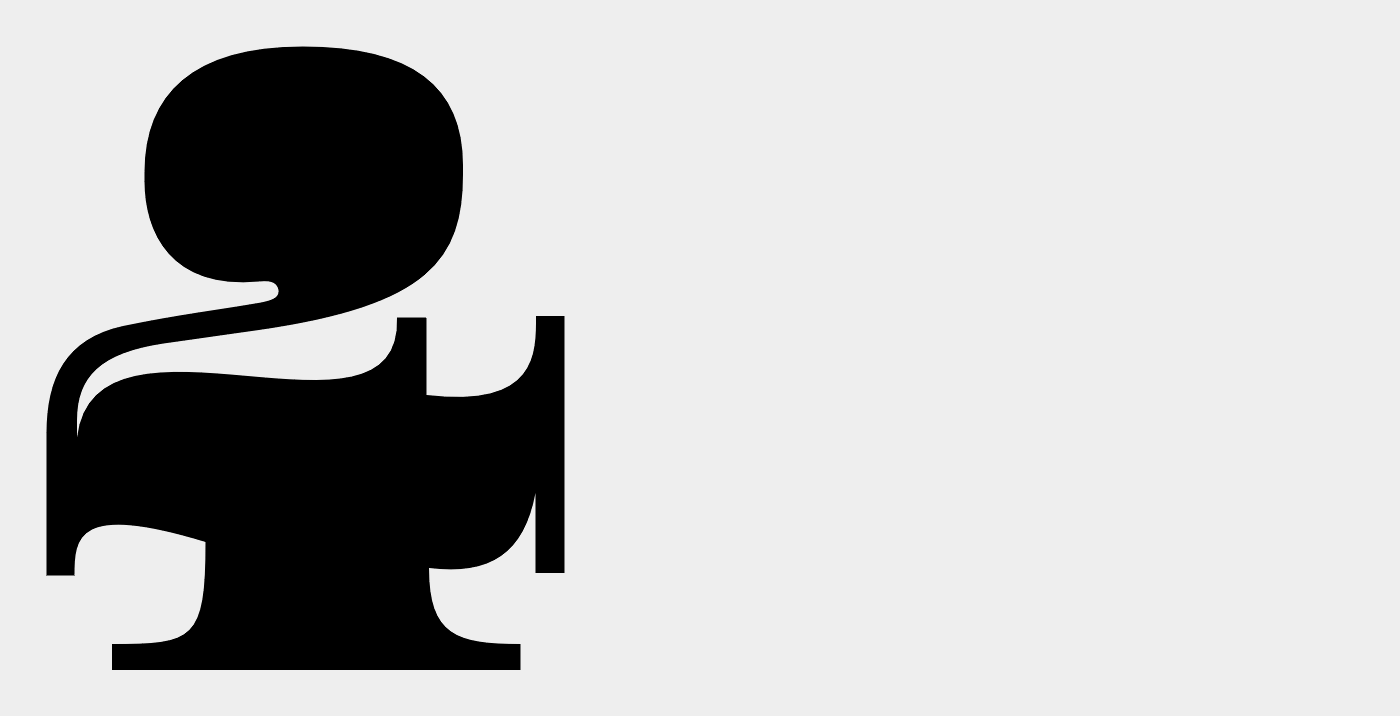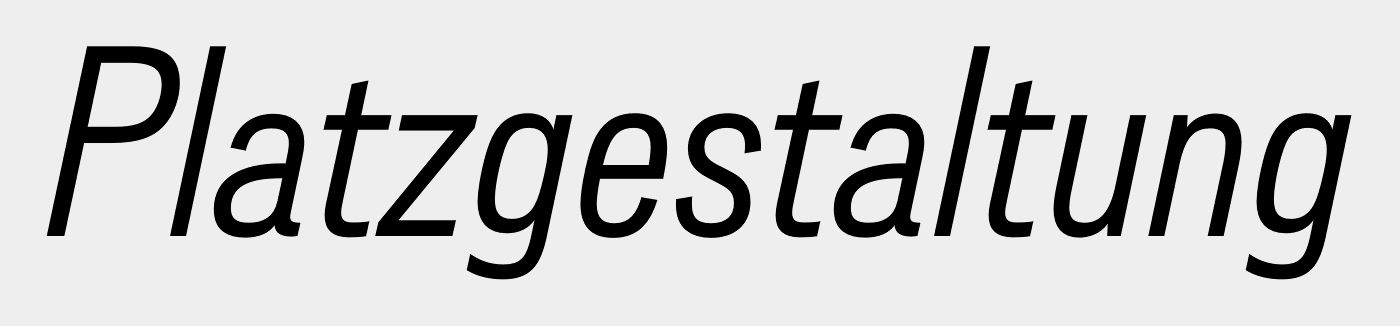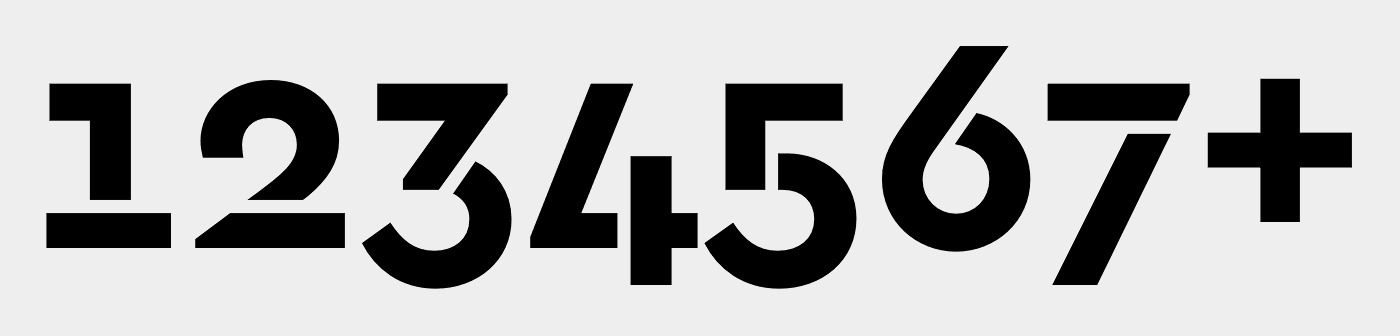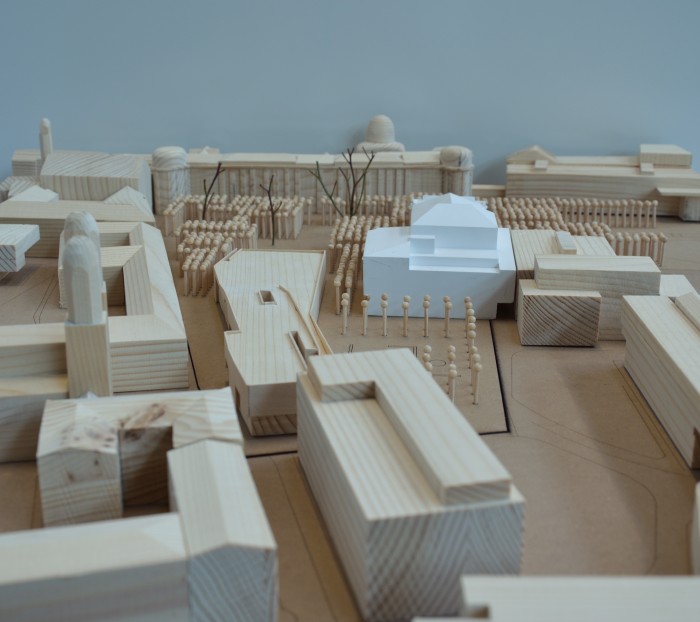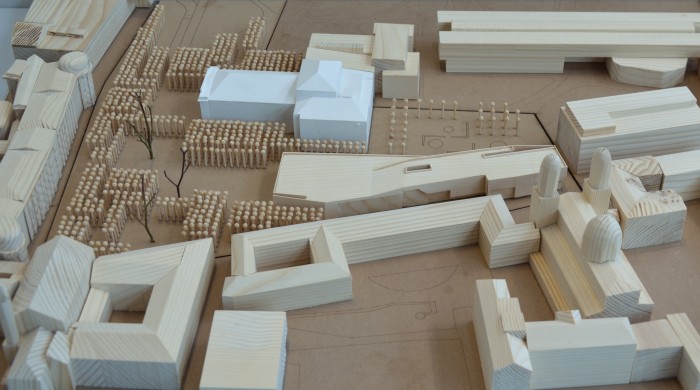
Suche Font für passende Zahlen
Es handelt sich um ein 'Haus der Musik' in dem 3 unterschiedliche Institute untergebracht sind - gemeinsamer Nenner Musik. Das Haus hat etwa 9000 m² groß und sehr lang und schmal - die Dachfläche begehbar. Materialisierung - Beton. Der Kontext ist städtisch - historischen. Bei der Platzgestaltung werden sehr viele Bäume eingesetzt werden.
Im Anhang sind zwei schnelle Modellfotos. Das längliche, organische Gebäude in der Mitte ist meines.
In die Arsenal-Didot-Kombination würde nämlich auch noch gut etwas Geometrisches passen, wenn es um Architektur gehen soll.
Aber noch schlüssiger fände ich eine Kombi in der Stencil- und Zusatzfont aus einer Familie stammen würden. Das ginge bei der Cera (auch ohne Stege erhältlich) – habe aber wegen den Kosten noch mal kurz für Dich gestöbert:
• kostenfreier Stencil-Schnitt, restliche Schnitte ca. 32 € und sowohl als Headline- als auch Textfont denkbar (dann könnte die Didot für die Überschrift bleiben)
• außerdem: »länglich, organisch«.  ;-)
Mir ist gerade noch etwas ganz Abgefahrenes untergekommen: Ein Font, der aus 112 verschiedenen Schnitten besteht – und jeder Schnitt enthält nur die Zahlen von 0 bis 9 und sieht vollkommen anders aus als die anderen 111 Schnitte. Der Hintergrund ist, dass der Gestalter Ziffern für Uhren im Sinn hatte, die ja oftmals freier gestaltet werden können, als dies bei Zahlen der Fall ist, die sich einer bestimmten Schrift unterordnen müssen. Vielleicht findet sich ja auch dort der perfekte Ziffernsatz für unseren Threaderöffner.